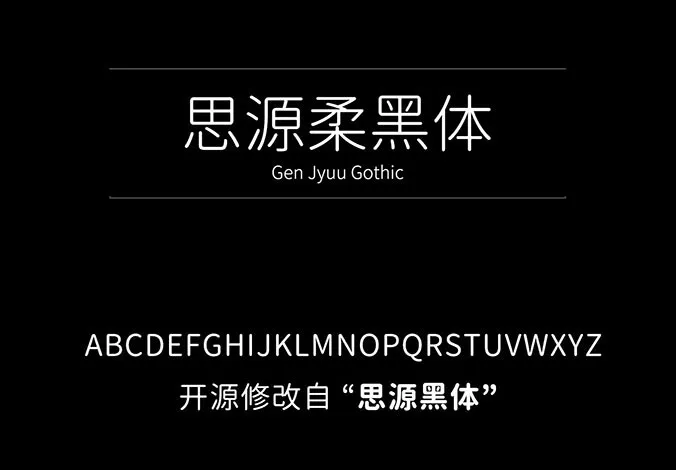
思源柔黑體(源柔ゴシック)和思源真黑體(源真ゴシック)是日本 自家製フォント工房基於開源字體“思源黑體”修改製作衍生而來,支持簡體中文、繁體中文以及日文三種語言。兩款字體都是開源免費的,應用場景非常廣泛。
思源柔黑體一共發佈了 3 個版本,分辨是標準版、L、X。它們的區別在於圓角的圓潤程度不同,L 圓角最小 (最尖),X 圓角最大 (最圓),而標準版則是介於兩者之間。每個版本都有 7 種字重,3種字形樣式 (包括等寬字體)。